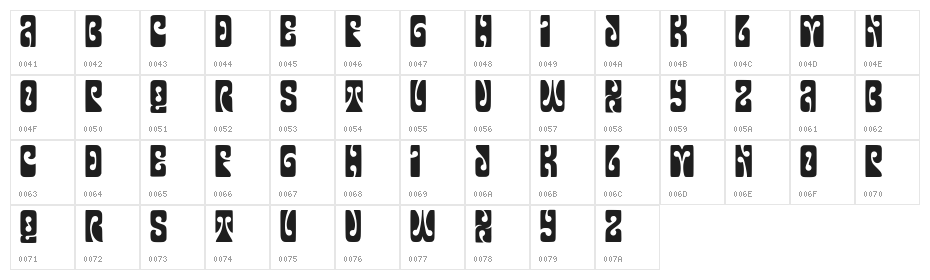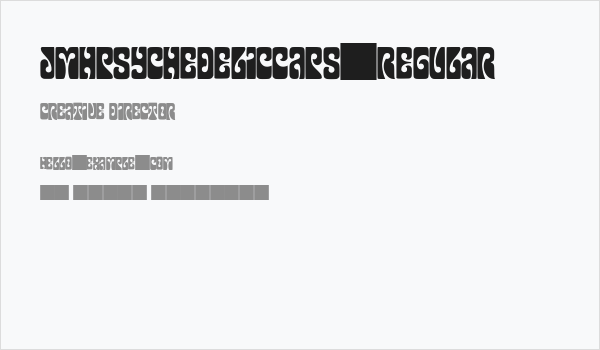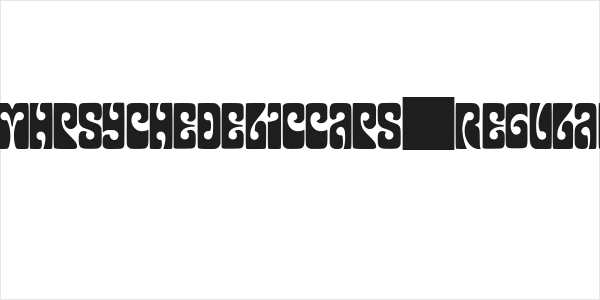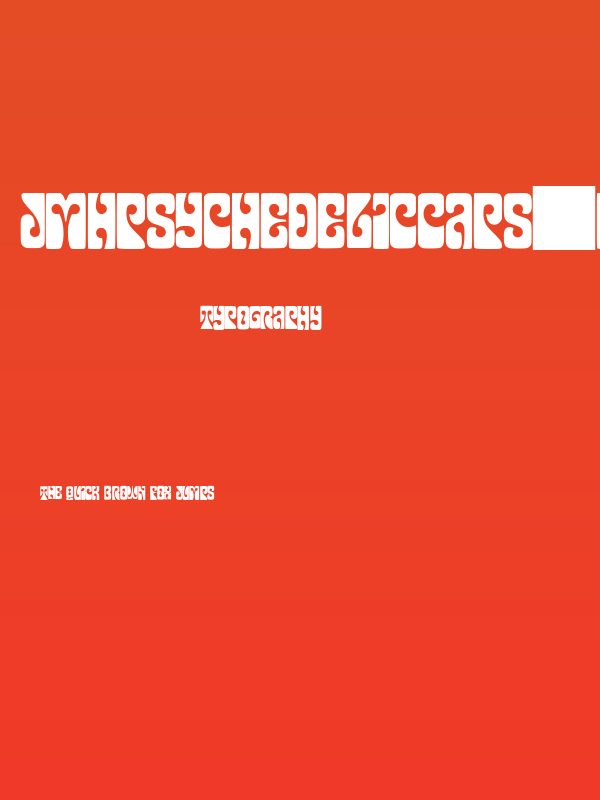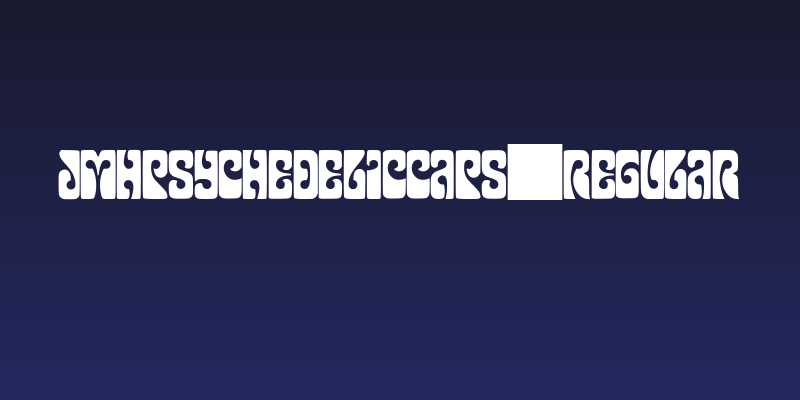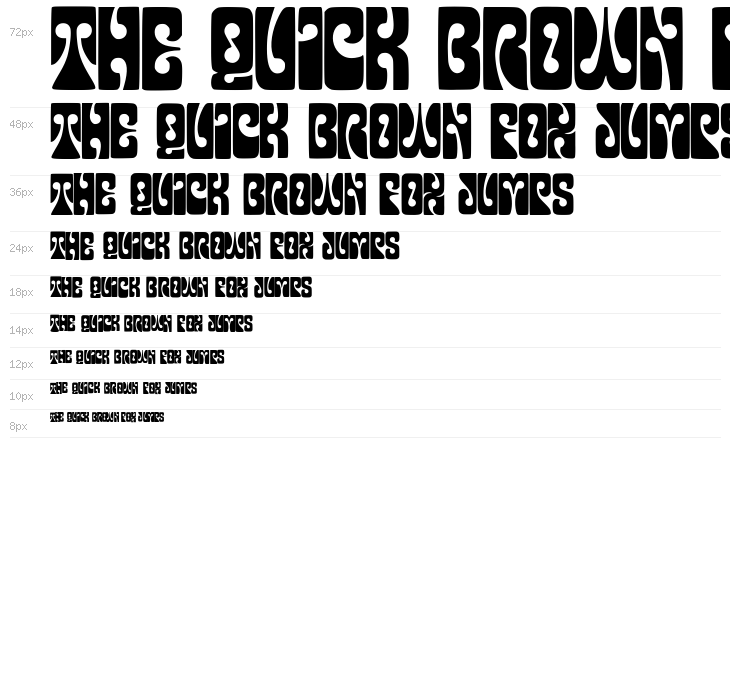
JMHPsychedelicCAPS-Regular Font
✎ Curly
| Estilo general | Vintage |
| Proyectos propuestos | Perfect for retro-themed posters, album covers, event flyers, and branding that seeks a vintage or psychedelic aesthetic. |